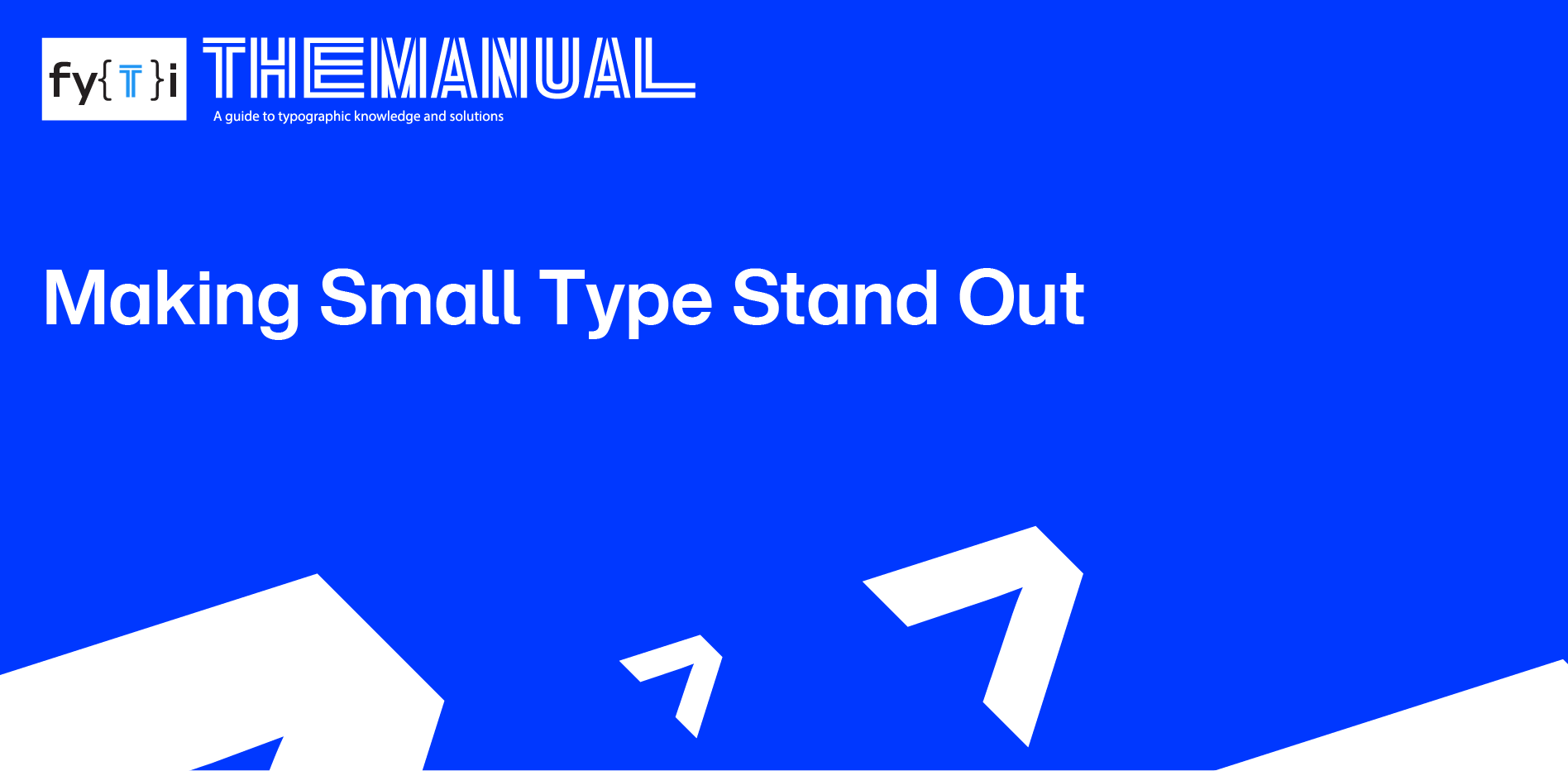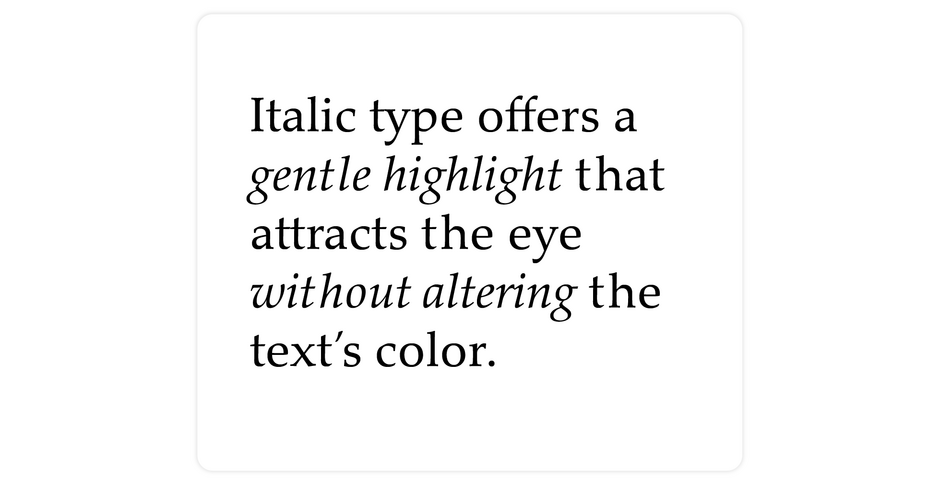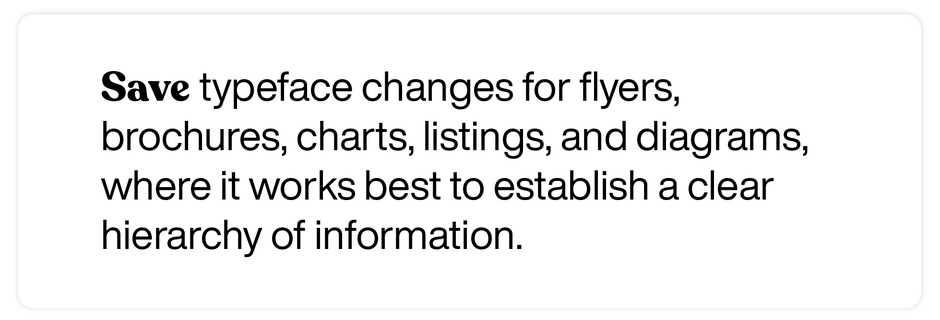
Manuel : Faire ressortir les petits caractères
La mise en valeur des textes - en particulier dans le texte courant - est un outil typographique puissant et important. Elle guide le lecteur à travers les blocs de texte, en l'aidant à repérer les mots spéciaux et les phrases clés. Il existe plusieurs façons de procéder. Pour des situations spécifiques, certaines sont meilleures que d'autres.
Italique
L'italique offre une légère mise en valeur qui attire l'œil sans modifier sensiblement la couleur du texte ni ralentir le processus de lecture. L'italique se fond harmonieusement dans le contenu environnant et peut être utilisé fréquemment dans un texte courant.
En cas d'utilisation de l'italique, il convient d'utiliser l'équivalent de la graisse romaine (droite) du texte qui l'entoure. Évitez les italiques gras. Elles sont plus difficiles à lire, surtout dans les passages longs.
Les caractères gras donnent une impression plus forte et plus affirmée que les italiques, mais ils doivent être utilisés avec parcimonie. Un contraste de poids excessif peut perturber la fluidité visuelle et produire un effet de "damier" gênant dans les blocs de texte.
Certaines familles de caractères ont des gradations de poids subtiles. Choisissez un caractère gras avec un saut important. Un changement de graisse subtil peut distraire et troubler le lecteur.
Type Taille
L'ajustement de la taille des caractères à l'intérieur d'un bloc de texte peut être un outil ludique et illustratif, à utiliser de préférence à des fins expressives. Toutefois, il n'est généralement pas recommandé de l'utiliser pour des textes continus.
Type Style
Changer de style de caractères est une bonne chose, mais pas tellement dans un texte courant. Réservez-le aux dépliants, aux brochures, aux tableaux, aux listes et aux diagrammes, où il permet d'établir une hiérarchie claire de l'information.
Couleur
La mise en couleur de certains mots ou de certaines phrases permet de mettre l'accent de manière visible et harmonieuse. Elle permet de faire ressortir le texte sans modifier le style typographique ou le formatage, tout en ajoutant un intérêt visuel à la conception. Il suffit de choisir les couleurs avec soin. Les couleurs vives ressortent, tandis que les textes de couleur claire s'effacent en arrière-plan.
Utilisez l'emphase avec parcimonie - un usage excessif dans un texte courant dilue son impact.
Enfin, le soulignement n'est presque jamais une bonne idée, sauf si vous voulez imiter une machine à écrire.